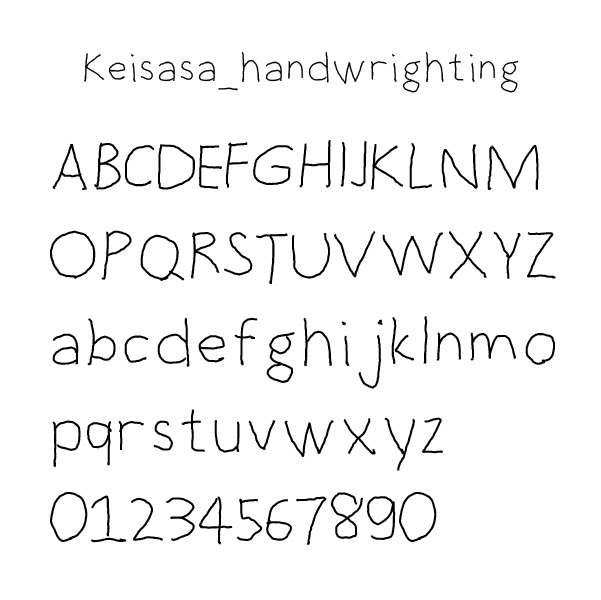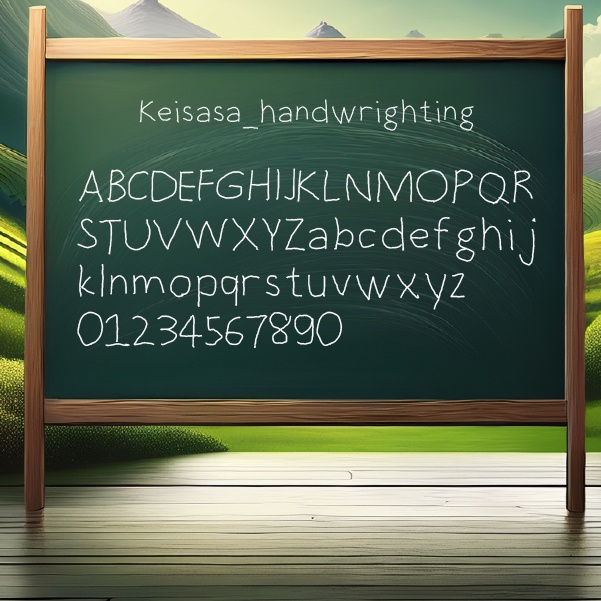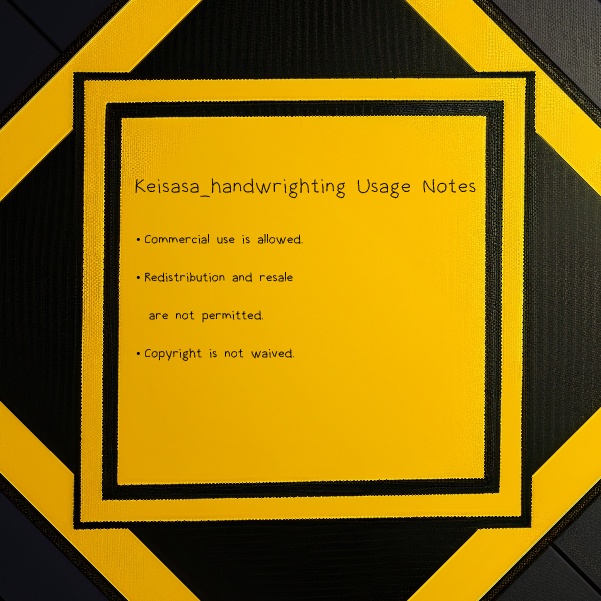
【商用可】Keisasa-handwriting.ttf|ゆるかわ手書き風フォント
Keisasa Handwriting Font Keisasa Handwriting Fontは、手書きの温かみと親しみやすさを感じさせるフォントです。ナチュラルでラフな線が特徴で、カジュアルなデザインや個性的なプロジェクトに最適。メッセージカードやポスター、SNS投稿、ロゴなど、幅広いシーンで使いやすいスタイルです。 スペック フォント形式:TrueTypeフォント(.ttf) スタイル:手書き風、カジュアル、ナチュラル 対応言語:日本語および英語(アルファベット) 使用可能なソフトウェア:Adobe Illustrator、Photoshop、InDesign、Microsoft Word、Google Docs など ライセンス:商用利用可能(個人・商業利用ともにOK) 特徴とこだわり Keisasa Handwriting Fontは、手書きの自然なタッチを大切にし、親しみやすく柔らかな雰囲気を持っています。ラフだけど整ったバランスがあり、ナチュラルな手書き感を演出しつつも、読みやすさをしっかり確保。あたたかみのあるメッセージや、手作り感を出したいデザインにピッタリです。 ロゴやタイトル文字、メッセージカードなどにも幅広く対応。日常のデザインに馴染む、使い勝手の良いフォントです。 制作の道のり 「手書きらしさ」と「使いやすさ」を両立させることを目指して制作しました。フリーハンドで描くような自然な流れを意識し、やさしさと親しみを感じるフォントに仕上げています。 制作中は、何度も線の太さや角度を調整し、自然さを追求しました。デジタルでありながらも、手書きの温かさを伝えるフォントになっています。 ライセンスについて Keisasa Handwriting Fontは、商業利用を含む幅広い用途にお使いいただけます。 ただし、フォントデータそのものの再配布や販売は禁止しています。 著作権は放棄しておりませんので、利用規約に沿った形でご利用ください。 締めの一文 手書きのぬくもりが、あなたのデザインをもっと魅力的にします。 ぜひ、Keisasa Handwriting Fontをあなたの次のプロジェクトにご活用ください! Keisasa Handwriting Font is a casual and friendly typeface that captures the warmth of natural handwriting. Its rough yet balanced strokes bring a personal, handmade feel to your projects. Perfect for message cards, posters, social media content, logos, and more. Specs Font Format: TrueType Font (.ttf) Style: Handwriting, Casual, Natural Languages Supported: Japanese and English (Alphabets) Compatible Software: Adobe Illustrator, Photoshop, InDesign, Microsoft Word, Google Docs, etc. License: Commercial use allowed (both personal and business) Features Keisasa Handwriting Font offers a natural hand-drawn look that adds warmth and charm to your design. Its casual and friendly style fits well in message cards, logos, and titles where a personal touch is key. Despite its handmade appearance, the font maintains excellent readability, making it versatile for many design needs. Development Story This font was designed to balance the charm of hand-drawn lines with ease of use in digital design. During development, careful attention was paid to stroke width and angle adjustments to achieve an organic and welcoming flow. Keisasa Handwriting Font embodies the warmth of handwritten text while remaining practical for both print and digital projects. License This font is available for commercial and personal use. However, redistribution or resale of the font file itself is prohibited. Copyright is retained by the creator, and usage must comply with the license terms. Closing Line Bring warmth and personality to your design with Keisasa Handwriting Font! Perfect for your next creative project. This is an original TTF font designed by Japanese artist Keisasa. Available for commercial use. Ideal for creative design, games, and more.